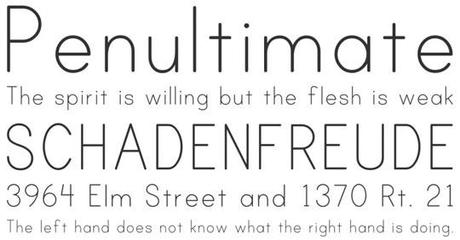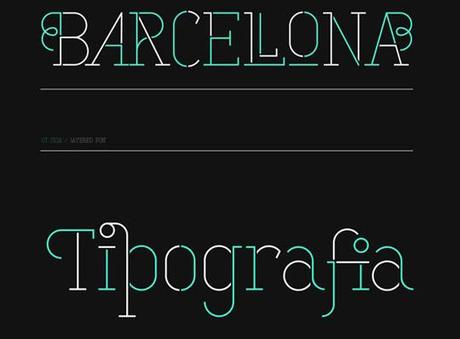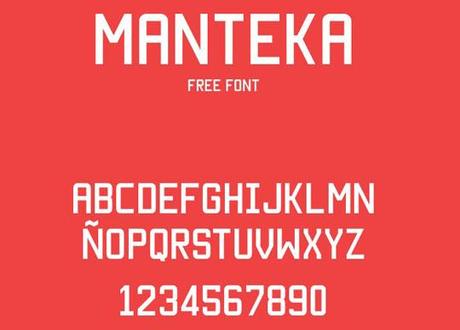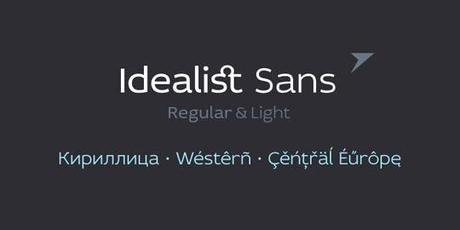
Designer Free Fonts #003
Nuovo appuntamento con la mia rubrica Designer Free Fonts, dove raccolgo i migliori font gratuiti da utilizzare nella costruzione di un web design unico e originale. Per ottenere, dalle nostre pagine web, un risultato di comunicazione efficace bisogna essere molto accurati nella scelta del font giusto. Il carattere con cui sviluppiamo un sito web, un progetto di print design o un poster deve essere semplice, facile da leggere e, nello stesso tempo, bello graficamente. Quindi la scelta del font da utilizzare nei nostri progetti, non risulta una operazione molto facile. Nel web, veniamo costantemente bombardati da una miriade di font gratuiti  che possiamo adottare nelle nostre pagine web o nella costruzione di un artwork, ma la scelta risulta lunga ed estenuante e spesso ci si accorge che il font, appena scaricato, non e’ completamente free e non e’ possibile utilizzarlo per progetti commerciali. Ecco, proprio per questo, ho deciso di scrivere questa rubrica intitolata Designer Free Fonts, dove raccolgo e seleziono i migliori font, veramente gratuiti, che potrete utilizzare per ogni progetto personale o commerciale che sia. Quindi se sei alla ricerca di un font fortemente comunicativo, libero dal copyright o, semplicemente, vuoi conoscere gli ultimi font usciti, rimani connesso con questa rubrica e sicuramente troverai il font che fa al caso tuo e che si adatta completamente al tuo design. Buona visione e buona scelta!
Idealist Sans
Un font semplice, facilmente leggibile dal design sobrio e pulito che si adatta ad ogni circostanza. Ideale per pagine web e progetti di print design molto curati ed eleganti.
Print Crearly
Questo free font e’ molto utilizzato nella stampa o nei progetti di print design. Molto scenico, riesce a dare la giusta forza al messaggio che vogliamo trasmettere. Elegante, sobrio e ordinato.
Manteka
Free font molto corposo che si puo’ utilizzare per banner eleganti e altamente comunicativi. Un font adatto ad un design diretto e forte che non disdegna l’eleganza.
Aleo
Questo font, personalmente, l’ho usato molto per progetti tipografici e costruzione di poster design. Carattere deciso, forte e molto comunicativo che riesce a rendere piu’ intenso il nostro messaggio.
Stela Regular
Font molto impegnativo e scenografico adatto ad un uso estremo della tipografia. Molto utilizzato per poster design in stile retro.
Conclusioni:
Hai appena visto la mia selezione di Designer Free Fonts. Non sono molti, ma sono dei font esageratamente utili nella vita quotidiana di un web e graphic designer. Pochi ma buoni, come si suol dire, e completamente gratuiti che puoi scaricare per ogni tuo prossimo progetto. Font eleganti, semplici e molto attraenti che si sposano con ogni tipo di design.